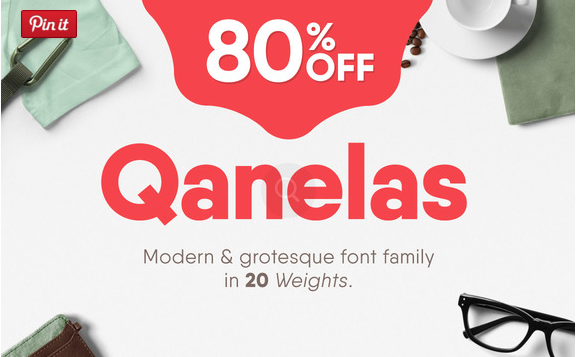
Qanelas Font Family + Web Fonts – Fonte Grátis
Qanelas Font Family + Web Fonts
A Qanelas é uma família de fontes séries modernas sem serif com um toque geométrico. Esta paleta de caracteres abrange 20 pesos diferentes e 10 tipos rectos, juntamente com seus itálicos complementares. Essa fonte traz a modernidade do tipo não-latin às páginas digitais sem deixar de manter uma pegada geométrica que destaca sua estrutura clara e sofisticada. Perfeita para uso em sites, logos e design gráfico, a Qanelas é um recurso indispensável para qualquer designer de grafismo que busca um tipo moderno e versátil. A Hamilton é o responsável pela criação desta paleta única e vibrante. Suas fontes não-latinas são projetadas com uma atenção cuidadosa aos detalhes, garantindo que cada caracter tenha a perfeição necessária para destacar em qualquer aplicação visual. Seja ela usada em elementos de interface ou design gráfico, a Qanelas se destaca por sua capacidade de oferecer tanto a sofisticação como a simplicidade necessárias para um sucesso no mundo digital atual.